I en verden, hvor visuel kommunikation er altafgørende, søger designere og kreative sjæle konstant efter elementer, der kan give deres arbejde en unik identitet og en mindeværdig kant. Blandt de mange værktøjer, der står til rådighed, har skrifttyper en særlig plads, da de formidler mere end blot ord; de formidler følelser, stil og attitude. Inden for denne mangfoldige verden findes en kategori, der er kendt for sin urokkelige styrke, rå æstetik og ofte en dyb forankring i en svunden æra: gangster skrifttyper. Disse skrifttyper er ikke blot et valg af font; de er et statement, en hyldest til en stil, der emmer af historiefortælling og karakter. Fra de dristige streger, der minder om tatoveringskunst, til de elegante, men kantede former, der kendetegner klassiske blackletter-stilarter, tilbyder gangster skrifttyper en palette af udtryk, der kan transformere ethvert design fra almindeligt til ekstraordinært. I denne artikel vil vi dykke ned i, hvad der definerer disse fascinerende skrifttyper, hvorfor de er så populære, og hvordan du bedst kan anvende dem til at give dine projekter et uforglemmeligt præg af autenticitet og kant.
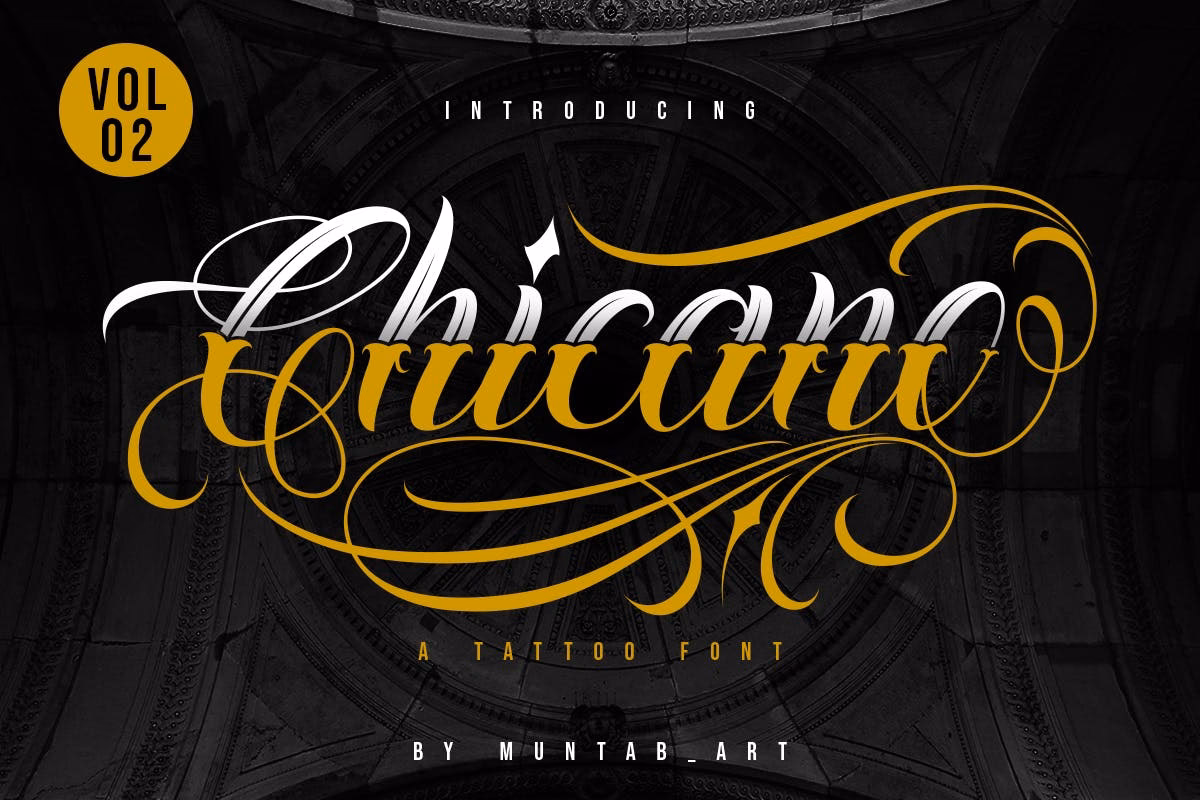
Hvad Gør en Skrifttype til en "Gangster" Skrifttype?
Betegnelsen "gangster skrifttype" refererer ikke til en enkelt, specifik stilart, men snarere til en bred vifte af typografier, der deler visse fælles æstetiske og tematiske træk. Kernen i disse skrifttyper er en følelse af styrke og robusthed. De er ofte kendetegnet ved deres dristige, tunge vægt, skarpe kanter og en generel fornemmelse af urokkelighed. Mange trækker inspiration fra historiske perioder, især det tidlige 20. århundrede, hvilket giver dem en karakteristisk vintage- eller retro-flair. Dette kan manifestere sig i alt fra art deco-inspirerede bogstaver til de mere rå og håndtegnede udtryk, der associeres med gadekultur og graffiti.
En anden definerende egenskab er deres evne til at formidle en bestemt attitude. Gangster skrifttyper er ikke subtile; de kræver opmærksomhed og udtrykker ofte en følelse af autoritet, oprør eller en rå, urban æstetik. De kan være inspireret af alt fra klassiske filmplakater til tatoveringskunst og motorcykelklubber. Deres visuelle sprog er rigt og ofte dramatisk, hvilket gør dem ideelle til at skabe en stærk visuel identitet. Uanset om det er gennem et blackletter-design med gotiske undertoner, en flydende script-stil, der efterligner håndskrevne notater, eller en fed, blokagtig sans-serif med et slidt udtryk, formår disse skrifttyper at indfange en særlig essens, der adskiller dem fra mere traditionelle skrifttyper.
Anvendelsesmuligheder: Hvor Passer Gangster Skrifttyper Ind?
På grund af deres markante udtryk er gangster skrifttyper utroligt alsidige og kan anvendes i en lang række designprojekter, hvor målet er at skabe en mindeværdig og karakterfuld visuel oplevelse. Deres evne til at fange øjet og formidle en specifik stemning gør dem til et foretrukket valg for designere, der ønsker at skille sig ud. Her er nogle af de mest populære anvendelsesområder:
- Branding og Logoer: Virksomheder, der ønsker at udstråle styrke, tradition eller en "undergrunds"-æstetik, kan drage stor fordel af disse skrifttyper. Et logo designet med en gangster skrifttype kan give et brand en uforglemmelig og genkendelig identitet, der signalerer robusthed og historie. Tænk på whiskey-mærker, barer, eller tøjbrands med en rå kant.
- Filmplakater og Teasere: Gangsterfilm, thrillere og historiske dramaer bruger ofte disse skrifttyper til at sætte den rette stemning allerede på plakaten. De formidler spænding, fare og en episk fortælling, hvilket trækker publikum ind. Skrifttyper som dem, der bruges i "The Godfather", er ikoniske eksempler på dette.
- Musik og Albumcovers: Inden for hip-hop, rock, metal og andre genrer, hvor udtrykket er råt og ægte, er gangster skrifttyper et naturligt valg. De kan afspejle kunstnerens persona og musikkens lyd, fra den graffiti-inspirerede stil til den mere tatoveringslignende skrift.
- T-shirt Designs og Apparel: Streetwear og modebrands, der henvender sig til et ungt og urbant publikum, anvender ofte disse skrifttyper for at tilføje et "cool" og oprørsk element til deres kollektioner. De er perfekte til grafiske tees, hættetrøjer og kasketter.
- Etiketter og Emballage: For produkter, der ønsker at udstråle håndværk, vintage-kvalitet eller en vis maskulinitet, kan gangster skrifttyper på etiketter og emballage skabe et unikt og tillidsvækkende udtryk. Forestil dig øletiketter, kaffeposer eller skægplejeprodukter.
- Tatoveringsdesign og Graffiti-kunst: Mange gangster skrifttyper er direkte inspireret af eller designet til at efterligne stilen fra tatoveringer og graffiti. De er populære blandt tatovører og graffitikunstnere, der ønsker at inkorporere en autentisk og genkendelig skrift i deres værker.
Find de Perfekte Gangster Skrifttyper til Dit Projekt
At finde den rette gangster skrifttype handler om at matche den visuelle stil med dit projekts budskab og æstetik. Der findes et utal af kilder online, hvor du kan udforske og downloade disse skrifttyper. Populære platforme som FontGet.com tilbyder et stort udvalg af gangster skrifttyper, og mange andre fontbiblioteker har lignende kategorier. Når du søger, vil du støde på både gratis og premium-muligheder. Det er afgørende altid at tjekke licensbetingelserne for hver enkelt skrifttype.
Mange gratis skrifttyper er kun licenseret til personlig brug, hvilket betyder, at de ikke må anvendes i kommercielle projekter (f.eks. logoer for virksomheder, produkter til salg). At bruge en personlig-brug-licenseret font i et kommercielt projekt kan resultere i juridiske problemer. Desuden kan gratis skrifttyper nogle gange mangle den fulde glyfunderstøttelse, OpenType-funktioner (som ligaturer og alternative tegn) eller den polering, man finder i professionelt designede premium-skrifttyper.
Premium skrifttyper som 'LHF Old Stock', 'Gangster label typeface' af Anton Antipov, 'Smoking typeface + Illustration' eller 'Chicano Font' tilbyder typisk en bredere vifte af funktioner, flere vægte og stilarter, og den nødvendige kommercielle licens, der giver dig ro i sindet. De er ofte designet af professionelle typografer og sikrer en høj kvalitet og konsistens. For seriøse kommercielle projekter, branding eller når kvalitet og juridisk sikkerhed er paramount, er premium-muligheder ofte den bedste investering.